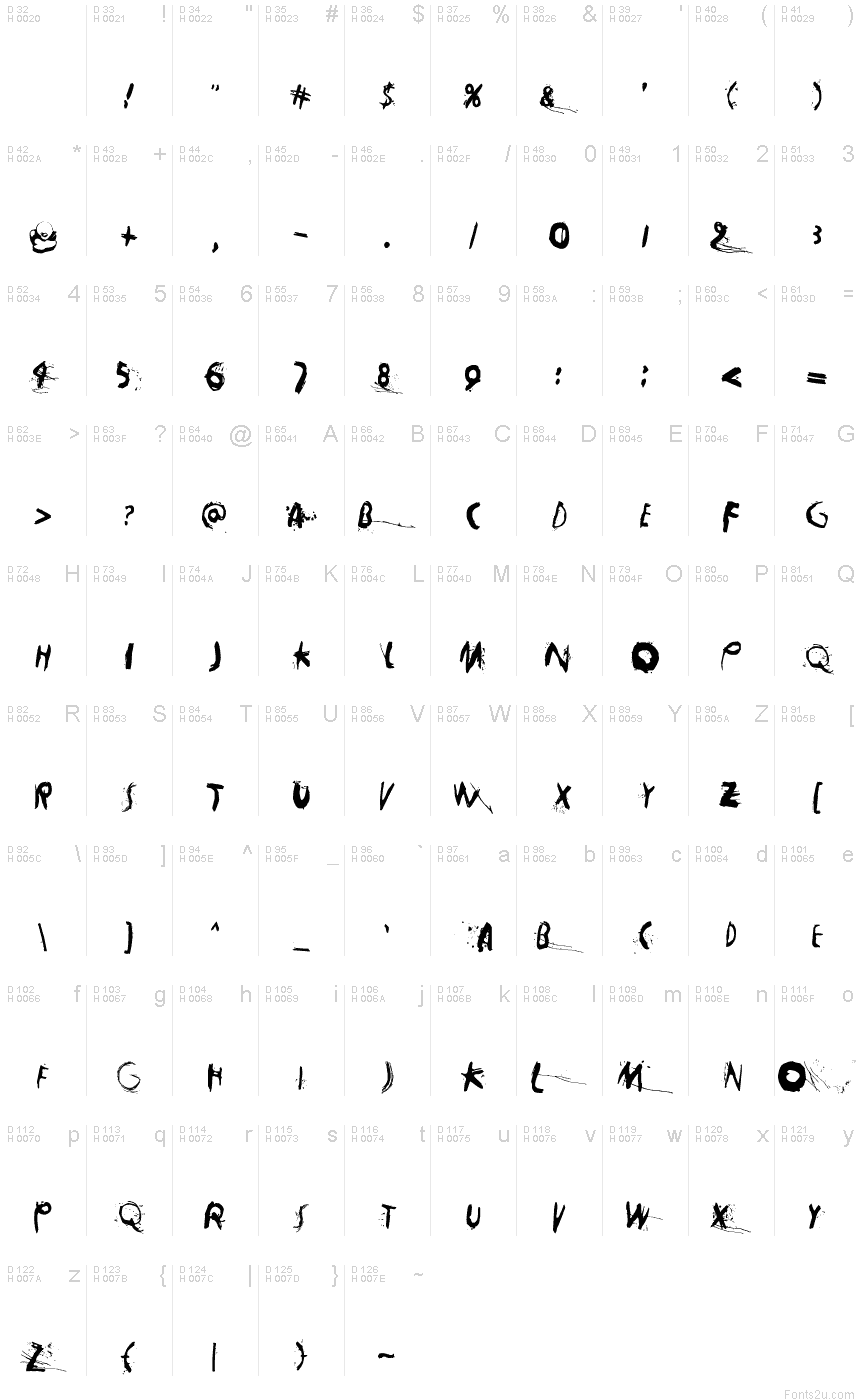
Horros di Junkohanhero è un font display gratuito in stile horror e distorto, che sembra uscito direttamente da un incubo. Macchie d'inchiostro spesse si scontrano con linee graffiate e arrampicanti, come se le lettere fossero state dipinte in fretta sul muro umido di una cantina. Gli schizzi sparsi e i tratti spezzati creano una tensione tattile e disordinata che crea istantaneamente un'atmosfera cupa e inquietante.
Con Horros, i tuoi titoli avranno un aspetto contaminato e instabile: è perfetto per locandine di film horror, volantini di Halloween, branding di escape room, titoli di giochi inquietanti, insegne di case stregate e grafiche per musica dark. Questo font gratuito rende al meglio in grandi dimensioni, dove gli schizzi e i graffi possono respirare; abbinalo a un font sans serif pulito e sobrio per il corpo del testo, in modo che il caos resti confinato al titolo, dove deve stare.